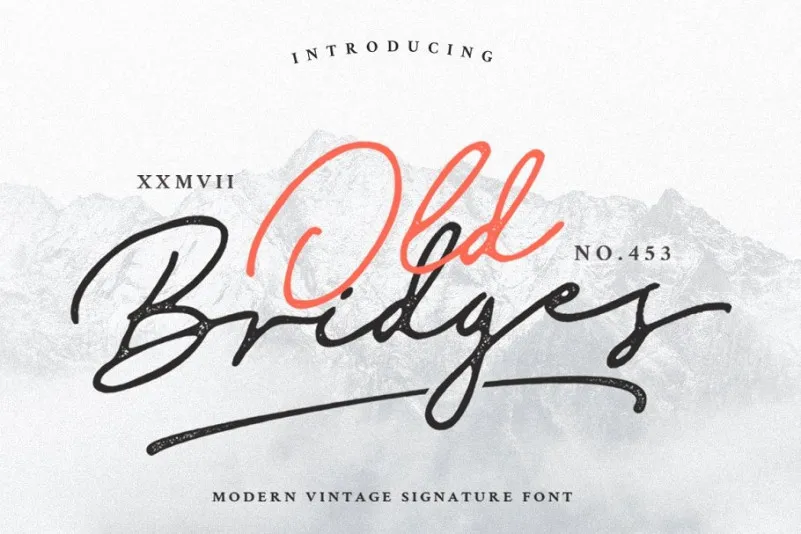
Old Bridges Signature Font – Download Grátis
Agradecemos pela consulta à Old Bridges Signature Font. Esta é uma tipografia script minimalista que traz uma elegante ligatura e alternativa de estilo. É perfeita para adicionar um look inovador e florido a qualquer design, especialmente se você está buscando uma fonte de escrita manual moderna com ligaturas e estilos alternativos prontos. Old Bridges Signature Font é perfeito para quem deseja criar escrever à mão sem precisar investir tempo na aprendizagem. Esta versão traz três estilos (Regular, Stamp, Rough), permitindo-lhe explorar diferentes opções de aparência para seus projetos. É uma fonte ideal para logos, frases escritas a mão, embalagens de produtos, cabeçalhos, cartazes, merchandising, mídias sociais e cartões de saudação. Old Bridges Signature Font é criada pela Vultype Co., uma marca que já se destacou com seu Modern Vintage Signature font. Esta fonte permite-lhe adicionar detalhes adicionais ao estilo da sua escrita à mão, como Swash personalizados, para tornar seus trabalhos ainda mais únicos e profissionais. Não importa o tipo de projeto que esteja a trabalhar, Old Bridges Signature Font é uma excelente escolha.